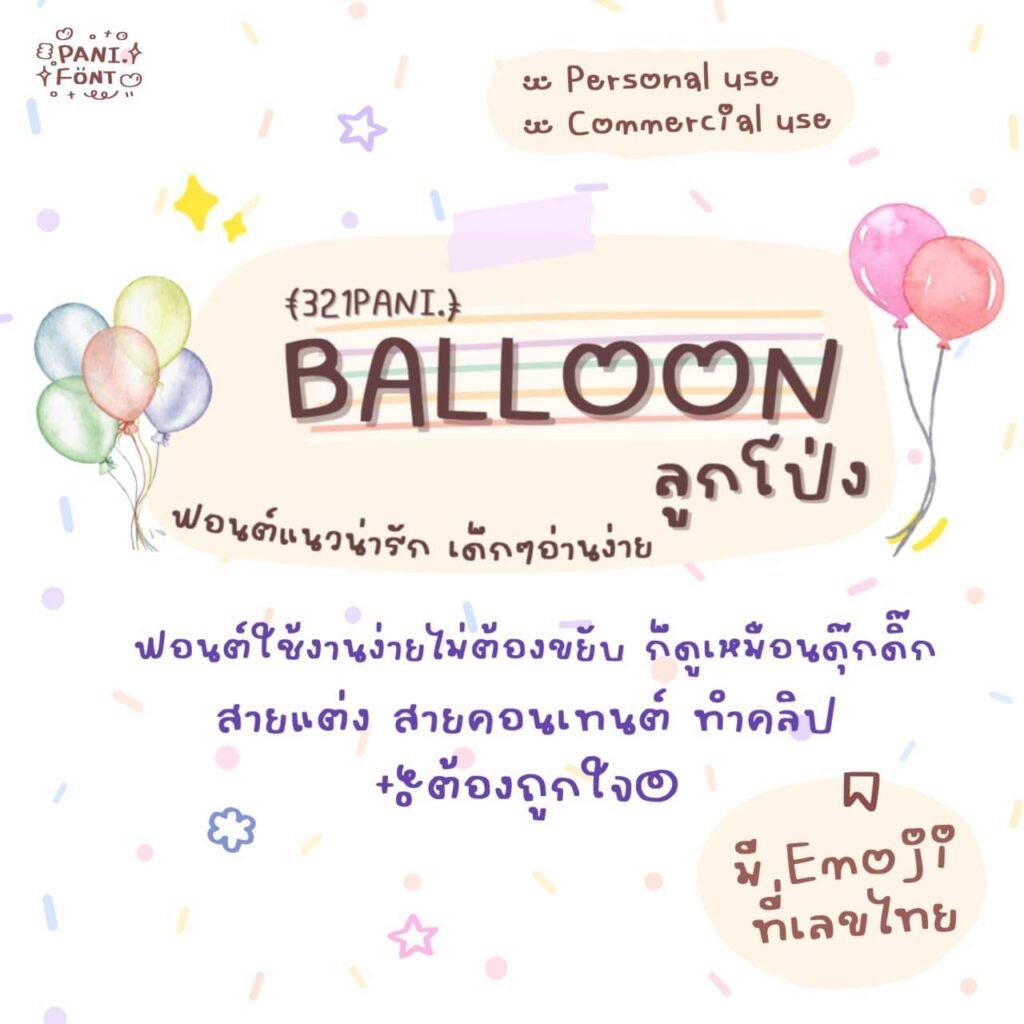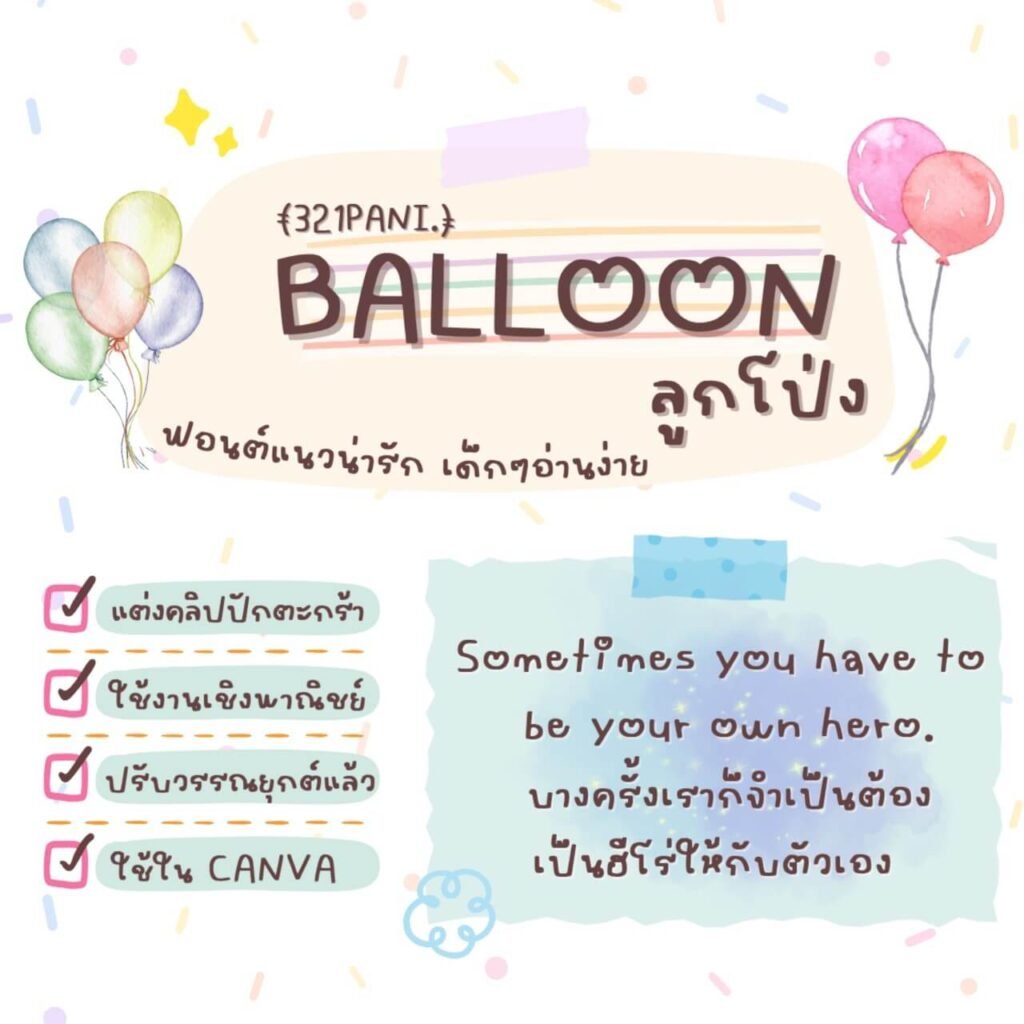
321PANI.Balloon
ฟอนต์ 321PANI.Balloon – โหลดใช้ฟรีตัว Demo ฟอนต์แนวดุ๊กดิ๊ก น่ารัก น่าชัง สายแต่ง สายคอนเทนต์ ทำคลิปไม่ควรพลาด!! จะใช้งานรายละเอียด ก็อ่านง่ายสบายตา